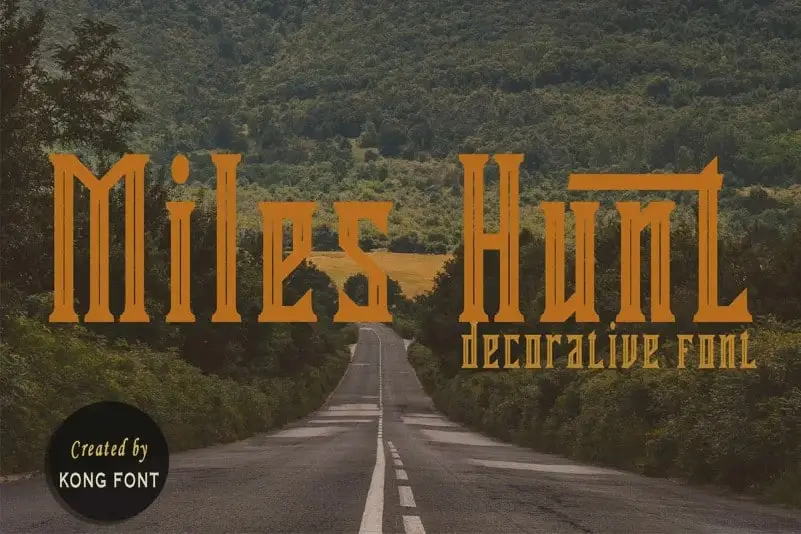
Miles Hunt Display Font – Fonte Grátis
Miles Hunt Display Font
A Miles Hunt Display Font é uma exuberante escolha para qualquer projeto que precisa destacar sua personalidade. Com seu estilo único entre as letras redondas e alegres, este tipo de display fornece um impulso visual instantâneo à página ou ao produto onde ele está presente. Adaptável às variáveis, essa fonte se adapta a diferentes tamanhos e formatos sem perder sua identidade peculiar. Ideal para marcas e banners, o Miles Hunt Display Font é perfeito para destacar seu conteúdo em ambientes digitais modernos, criando um impacto imediato que chama atenção dos usuários. Seja para criar um design atraente ou para uma campanha de marketing agressiva, este tipo exibe sua versão mais forte e poderosa, fazendo com que qualquer espaço seja o centro das atenções.